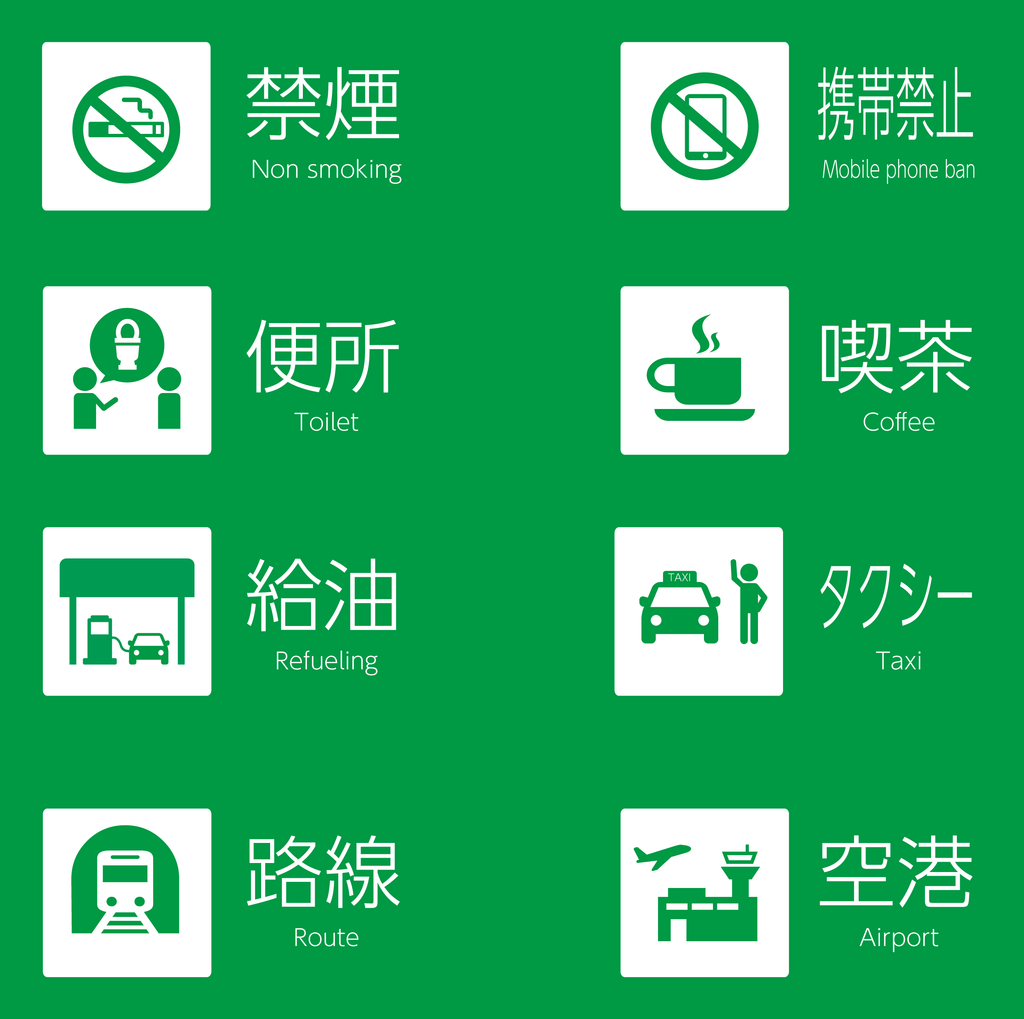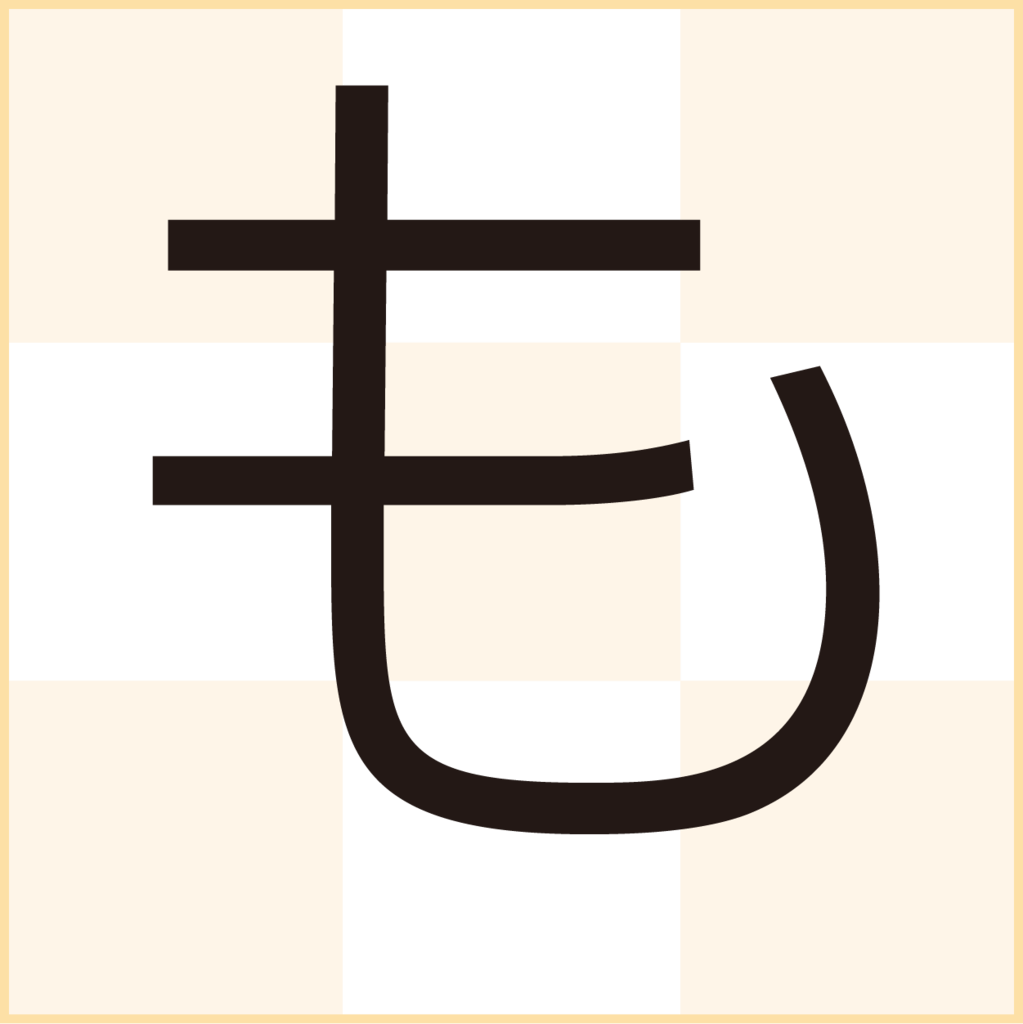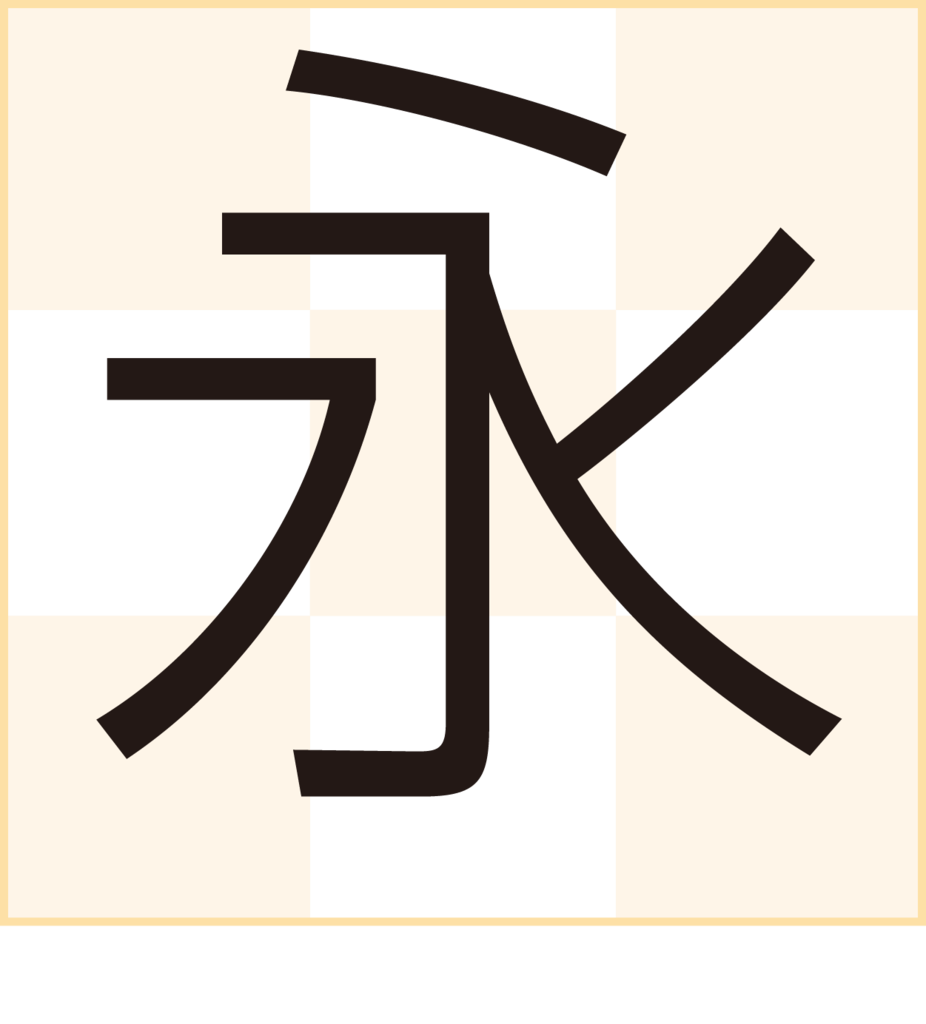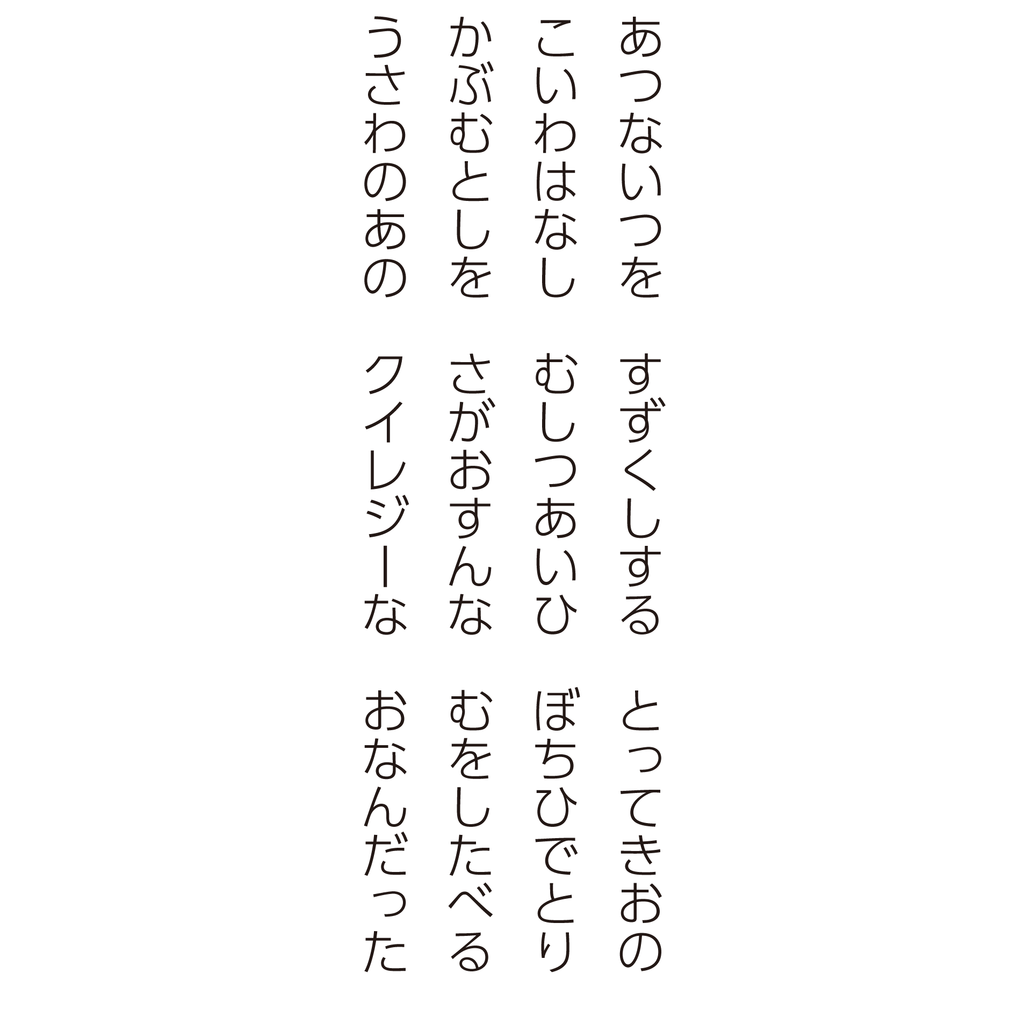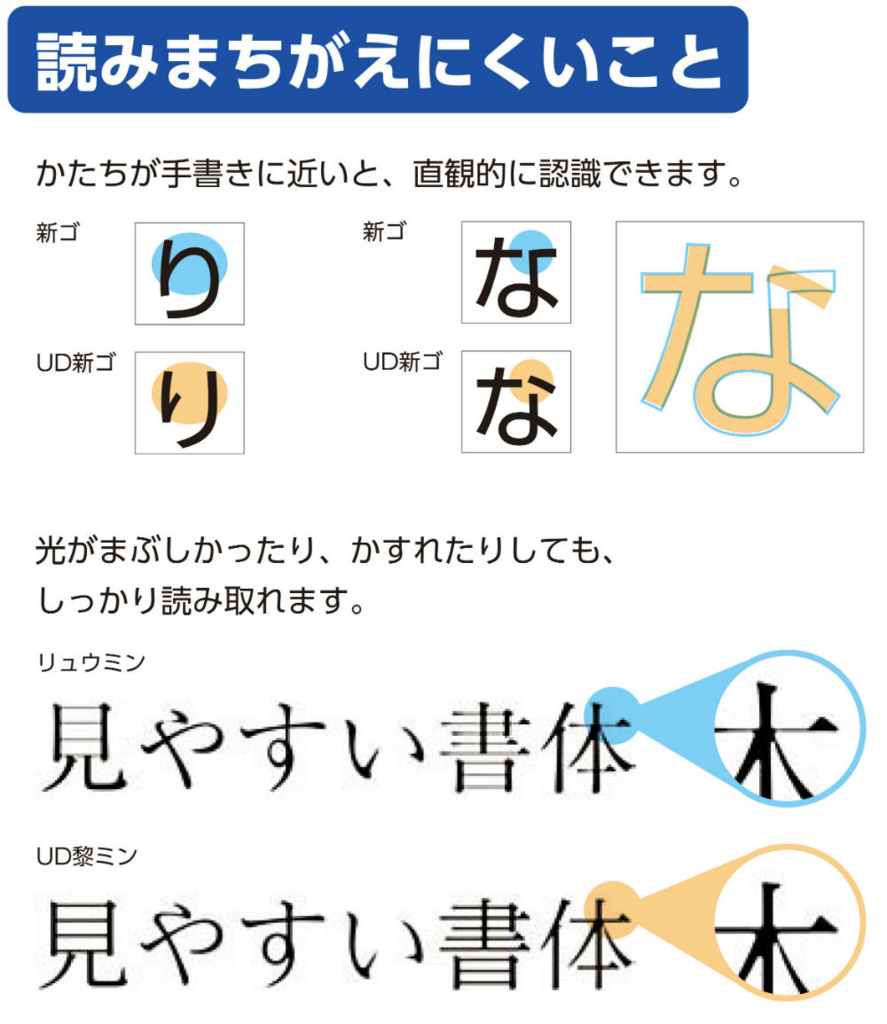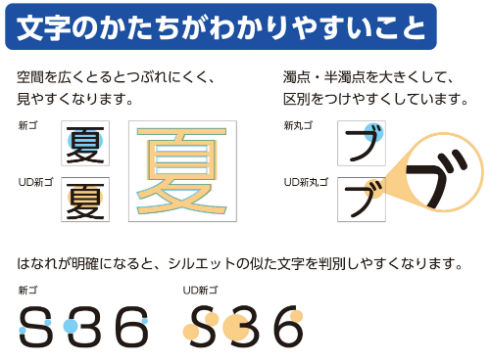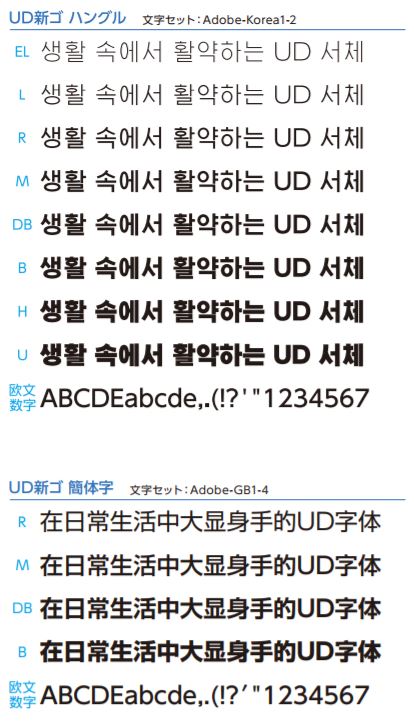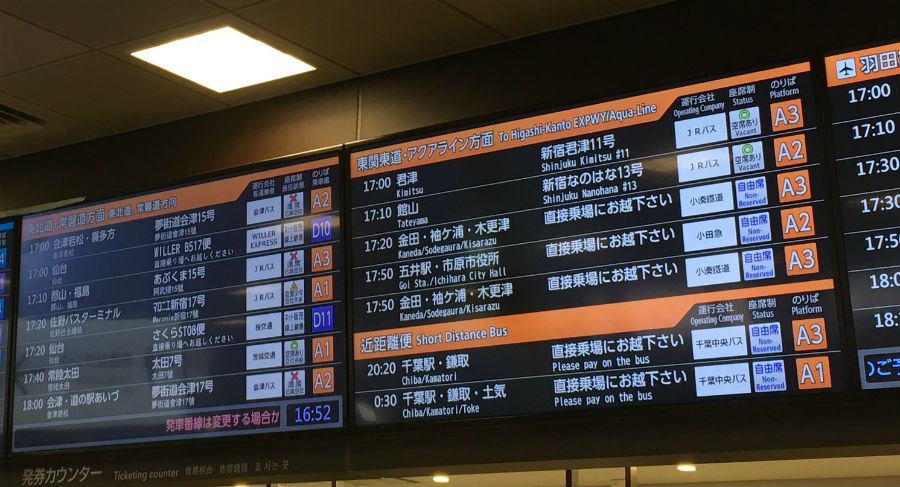
UD新ゴ
見やすい書体として評価の高い「新ゴ」をベースに、個々の文字のわかりやすさを重視した字形をとりいれた、モリサワのUD(ユニバーサルデザイン)書体。
欧文・数字には判別性にすぐれた欧文書体 ClearTone SG のデザインを採用しており、ユニバーサルデザインに配慮をしたい媒体で、見出しやサインなど整然としたデザイン的な表現において特に力を発揮する。
UD新ゴの書体見本
ハングルフォント「UD新ゴ ハングル」
「UD新ゴ ハングル」は、和文書体「UD新ゴ」をベースに設計された、ゴシック体のハングルフォント。ハングルとしての造形的なバランスを保ちながら「UD新ゴ」同様ふところを広く設計することで視認性を高め、また横組だけでなく縦組での軸や字幅なども考慮し、縦横どちらの組み方向でも読みやすい設計になっている。「UD新ゴ ハングル」は、「UD新ゴ」とデザインが揃って見えるように設計されており、ウエイトも「UD新ゴ」に合わせて8ウエイトが用意されているため、日本語とハングルを併記する場面でも、言語間のデザイン差が生じることがない。
中国語簡体字フォント「UD新ゴ 簡体字」
「UD新ゴ 簡体字」は、和文書体「UD新ゴ」をベースに設計された簡体字フォント。「わかりやすく」、「読み間違えることがない」というモリサワUD書体の基本的な考え方を踏襲して「UD新ゴ」同様ふところを広く設計することで視認性を高めている。「UD新ゴ 簡体字」は、「UD新ゴ」だけでなく、「UD新ゴ ハングル」ともデザインが揃って見えるように設計されているため、日英中韓の4ヶ国語表記の際にも統一したイメージの展開が可能となる。多言語の制作物にも活用できる書体。
中国語繁体字フォント「UD新ゴ 繁体字」
「UD新ゴ 繁体字」 は和文書体「UD新ゴ」のデザインをベースに設計されたゴシック体の繁体字書体で、台湾、香港、マカオでの中国語表記をサポートしている。2015年にリリースされた「UD新ゴ 簡体字」と合わせて使用することで中国語話者圏に広く対応する。「UD新ゴ 繁体字」は、台湾の国字標準字体に則った字体を採用している。
「UD新ゴ」シリーズとの併記を目的として作られたサンセリフ多言語フォント「Clarimo UDシリーズ」
「Clarimo UDシリーズ」は、和文・簡体字・繁体字およびハングルまで展開されている「UD新ゴ」シリーズとの併記を目的として作られたサンセリフ書体の多言語フォント。シンプルかつ可読性を重視した設計を特徴としている。それぞれの文字に精通した海外デザイナーが制作に携わり、高品質で統一感のある表現を可能にしている。
汎ヨーロッパ文字セットフォント「Clarimo UD PE」
ラテンアルファベットに加えてキリル文字、ギリシャ文字、およびベトナム語用文字を カバーする独自規格「PE」(汎ヨーロッパ)の文字セットを採用している。ExtraLightからUltraまで8ウエイトと幅広く、本文から標識表示など、さまざまな媒体で用途を問わずご利用できる。
アラビア文字フォント「Clarimo UD Arabic」
アラビア文字は主にアラビア語、ペルシア語、ウルドゥー語の表記に使われ、右から左に読む文字。類似字形の書き分けや、ふところ・開口部を広く保つなど読みやすさの工夫のほか、通常の字形では閉じているループを開くことで小級数、低解像度でも潰れない処理がなされている。また、異体字や合字、専用記号を多く備えており、細やかな表現が可能。
デーヴァナーガリー文字フォント「Clarimo UD Devanagari」
デーヴァナーガリー文字は、主にヒンディー語、ネパール語を表記するための文字で、それ以外にもインドの多くの言語を表記するのに用いられている。Clarimo UD Devanagariは明確な形状、ふところ・開口部を広く保つなど、読みやすさの工夫がなされている。さまざまな異体字やバリエーション豊かな合字を備えており、日常的な用途に限らず幅広い場面で利用できる。
タイ語フォント「Clarimo UD Thai」
「ループ」と呼ばれる丸い部分がある、スタンダードスタイルのタイ文字です。タイでは本文などのテキストによく使われる。Clarimo UD Thaiは、形状の曖昧さをなくすなど、読みやすさの工夫がなされている。また、タイ語で使用頻度の高いイタリックを備えており、組版の際に細やかなニュアンスまで表すことができる。
モダンスタイルタイ語フォント「Clarimo UD Thai Modern」
「ループ」と呼ばれる丸い部分がない、モダンスタイルのタイ文字。タイでは見出しや強調によく使われる。Clarimo UD Thai Modernは、形状の曖昧さをなくすなど、読みやすさの工夫がなされています。また、タイ語で使用頻度の高いイタリックを備えており、組版の際に細やかなニュアンスまで表すことが出来る。
モリサワが自社のUDフォント「UD新ゴ ハングル」の可読性に関する比較研究報告を公開
株式会社モリサワは「UD新ゴ ハングル」の可読性に関する比較研究報告を公開することを9月27日に発表した。
モリサワでは、慶應義塾大学と共同で、弱視者を含む多くの方を対象としたユニバーサルデザイン書体(UD書体)の読みやすさに関する比較研究実験を行っており、今回、多言語フォントのUD書体「UD新ゴ ハングル」の比較研究実験を韓国語を母国語とする晴眼者・弱視者を対象に複数のハングル書体を用いて行った結果、比較した書体の中で最も読みやすいことが検証された。 なお、「UD新ゴ 簡体字」「UD新ゴ 繁体字」(開発中)についても同様の実験を行い、順次結果を公開する予定。
「文字のかたちがわかりやすいこと」「読みまちがえにくいこと」「文章が読みやすいこと」をコンセプトに開発され、2009年11月のリリース以来、ユニバーサルデザインを意識した様々な媒体で採用されている。比較研究報告は、元となった書体や同カテゴリの書体と比較した時の読みやすさ、判別のしやすさに関するエビデンス(学術的研究結果)をまとめたものになっている。 この研究は第三者機関である慶應義塾大学心理学教室中野泰志教授と共同で実施されている。実験の結果、弱視者を含む多くの方にとって、モリサワUD書体は、比較対象書体と比べた時により判別しやすく、情報などを効率的に読むことができる書体であるとがわかった。
「UD新ゴ」に関する記事「交通機関の表示が見やすいUD(ユニバーサルデザイン)フォント化が進行中」
7月12日に「ITmedia NEWS」に掲載された記事「毎朝見てたはずなのに……知らない間に変わっていた駅の“アレ” 制作会社「気付かれなくていいんです」」が同日ヤフーニュースの経済欄にも転載される程、注目を集めている。
この記事によると、駅の券売機やバスの行き先といった交通機関で表示されるフォントが着々と新しいフォントに置き換えられていっていることが伝えられている。
置き換えられている新しいフォントとして、モリサワのUD新ゴが挙げられ、株式会社モリサワエンタプライズ事業部・園田晋さん、広報宣伝部・澤村明子さんが取材を受けている。
UD新ゴとは
モリサワのゴシック体である「新ゴ」をベースに、個々の文字のわかりやすさを重視した字形をとりいれたユニバーサルデザイン書体。欧文・数字には判別性にすぐれた欧文書体 ClearTone SG のデザインを採用している。ユニバーサルデザインに配慮をしたい媒体で、見出しやサインなど整然としたデザイン的な表現にオススメ。
園田さんによると「JR東日本の券売機に使われているのは、モリサワのUD新ゴです。バスタ新宿にある電光掲示板の行き先表示などにも同じフォントが使われています」とのこと。
また任天堂ゲーム機「Nintendo Switch」やキングジムの「ポメラ DM200」などにも採用されている。
「モリサワでは、性別・年齢・視力の強弱を問わず、誰でも読みやすいフォントをユニバーサルデザインと考えています」と澤村さんは語る。
モリサワのUDフォント制作は、フォントよりも視認されやすい「手書き文字」に全てのデザインを近づけていき、小さくしても潰れないよう濁点や半濁点は大きく線1本1本の間隔は広くしている。また文字全体のバランスを見直している。また、明朝体や長体をかけるゴシック体は横線が潰れないよう10%刻みで線の太さも調整していることなど細かなこだわりの部分も披露された。
こうした読みやすい文字を開発し駅などに広めている背景には「日本社会の高齢化」があるという。
「読みやすい文字はこれまで金融や医薬品など、読み間違いが人生を左右しかねない現場で必要とされてきました。しかし、高齢化によってその需要が社会全体に広がってきています」と園田さんは語る。